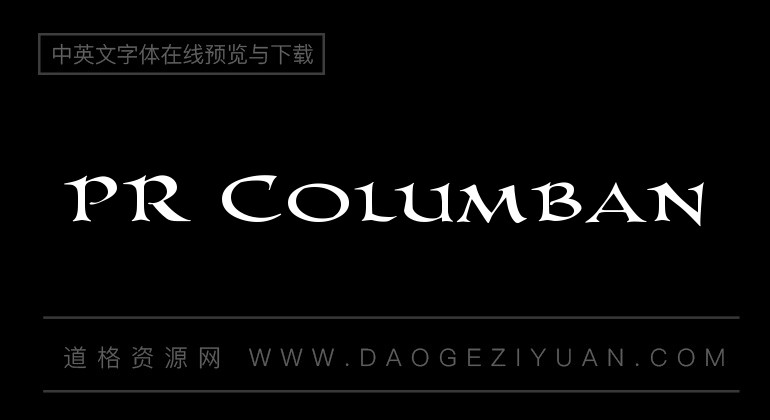
PR Columban 是一款由美国设计师 Patrick Ronan 创作的字体,它的外观简洁大方,主要用于报纸、杂志以及宣传册等文档的排版。它是一款综合性字体,可以用于各种风格的文档,既可以用于正式文书,也可以用于报纸、杂志等报道文章。它的字形简洁,有着清晰的线条,极具美感,可以给文档增添一份独特的魅力。内容介绍
PR Columban是一款非常不错的手写艺术字体,具有很好的视觉感,适合于文化类的宣传设计、商业类品牌的广告和产品包装设计以及个性化文字排版等较多场景。